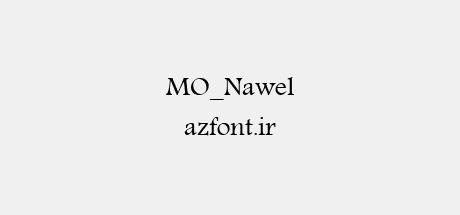
MO_Nawel
فونت زیبای رایگان MO_Nawel
قلم زیبای MO_Nawel از سری قلم های بسیار زیبا برای تایپوگرافی و لوگو تایپ می باشد.این قلم در وزن Regular و توسط www. toolps.blogspot.com طراحی و منتشر شده است.